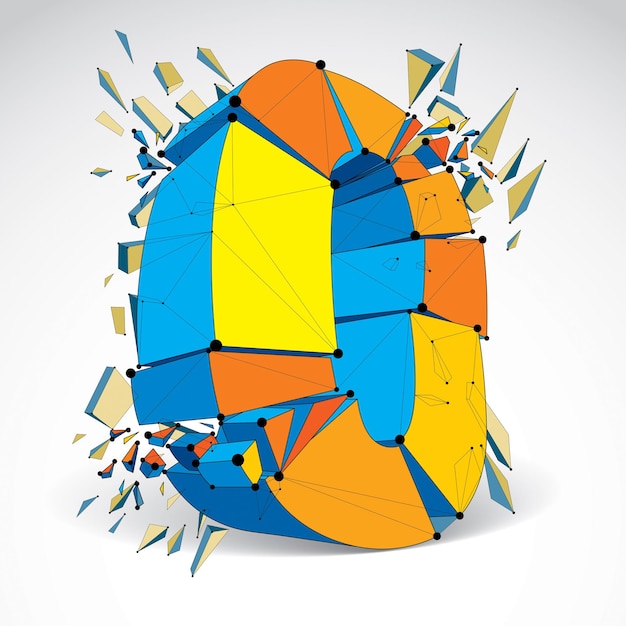
3d vektori low poly nolla numero mustilla yhdistetyillä viivoilla ja pisteillä, geometrinen lankaverkko fontti fragmenteilla. Perspektiivi säröillä numero langalla.